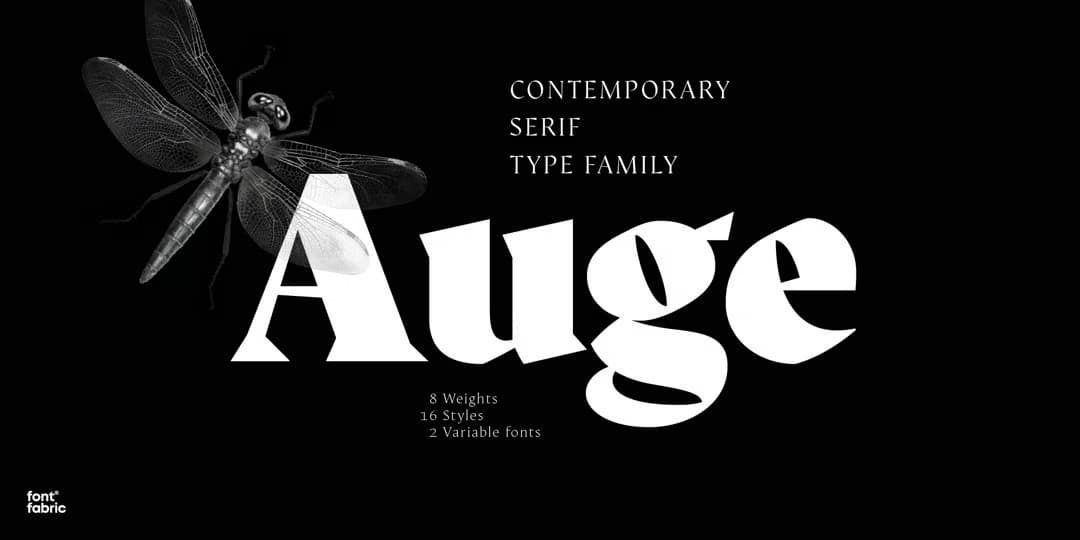
Auge
ちょっと変わったスタイルのコンテンポラリーローマン。アウトラインがシャープで、カーブにも滑らかではなくクッと折れ曲がった箇所があったりする個性的な書体で、セリフも大きなウェッジ型のものが付いている。雰囲気はクールかつシャープで、ウェイトは多いもののやっぱり本文よりはディスプレイ向きだろう。キリル文字もサポート。名前はドイツ語で「眼」の意味らしい。8ウェイト。